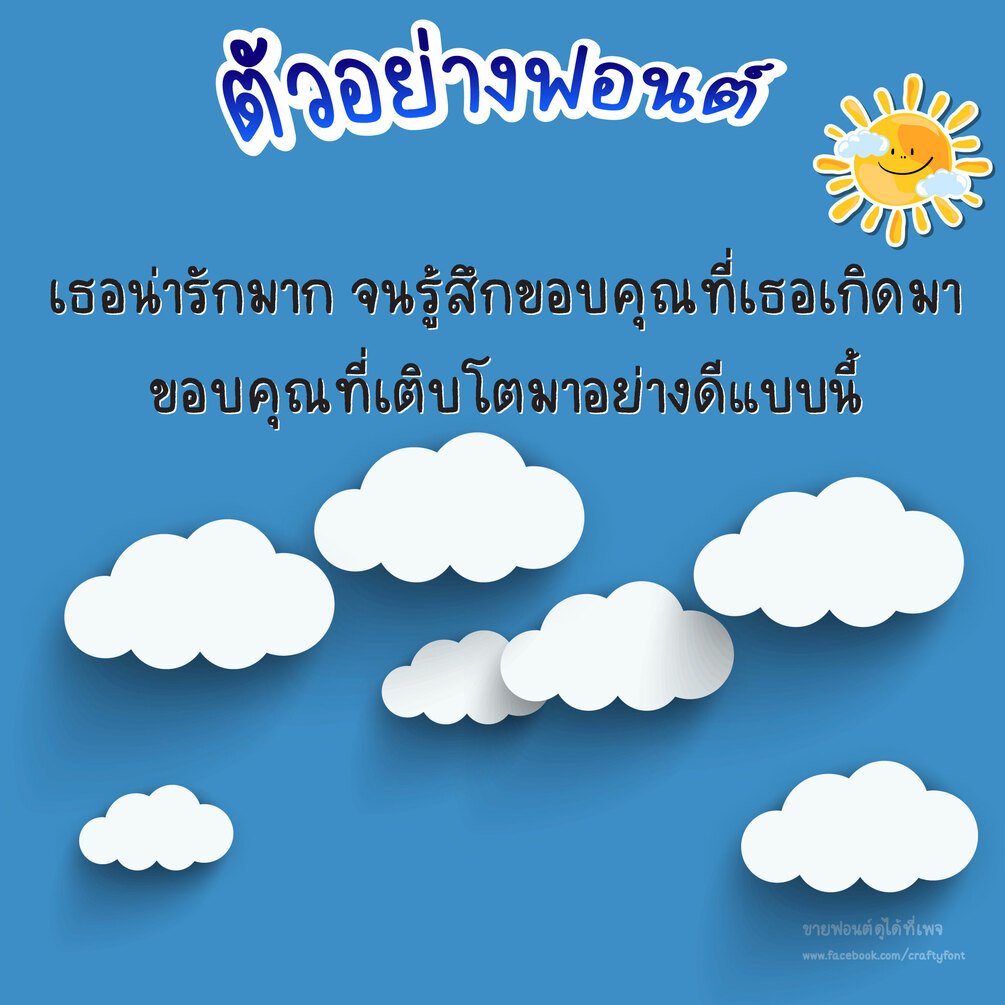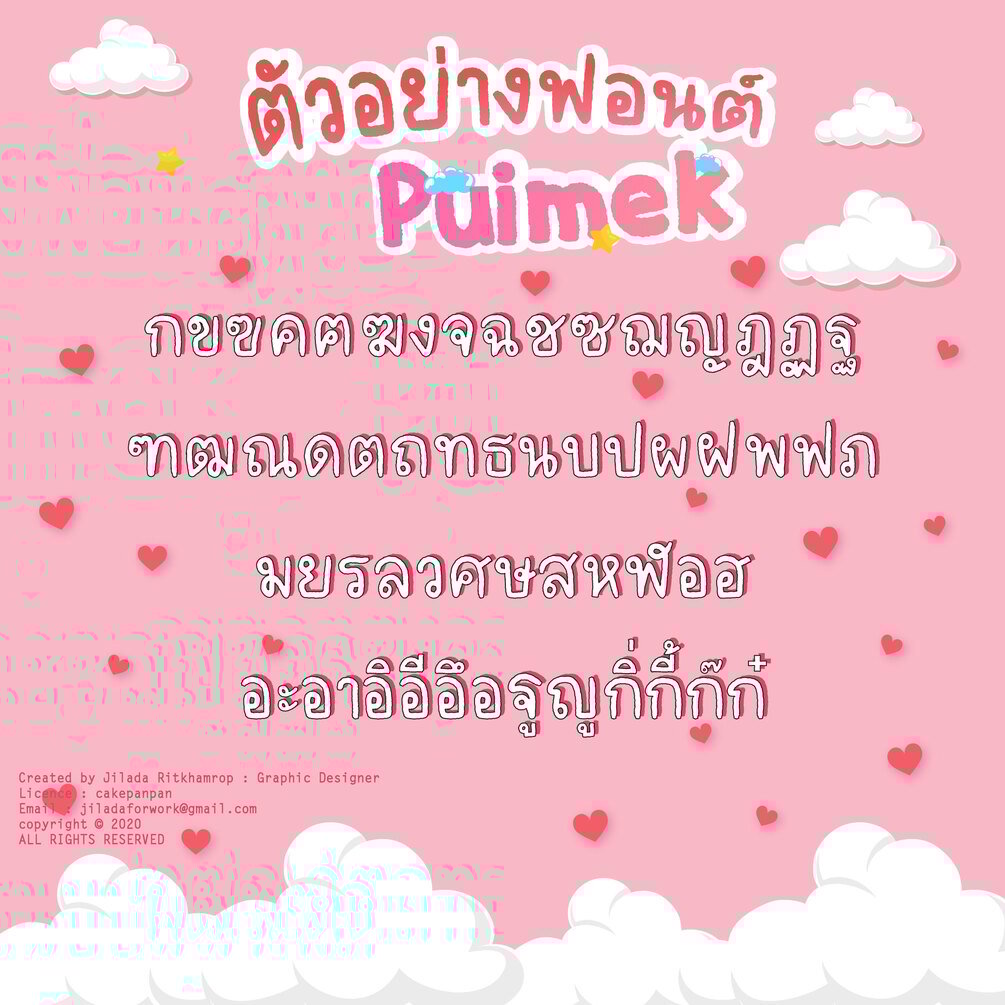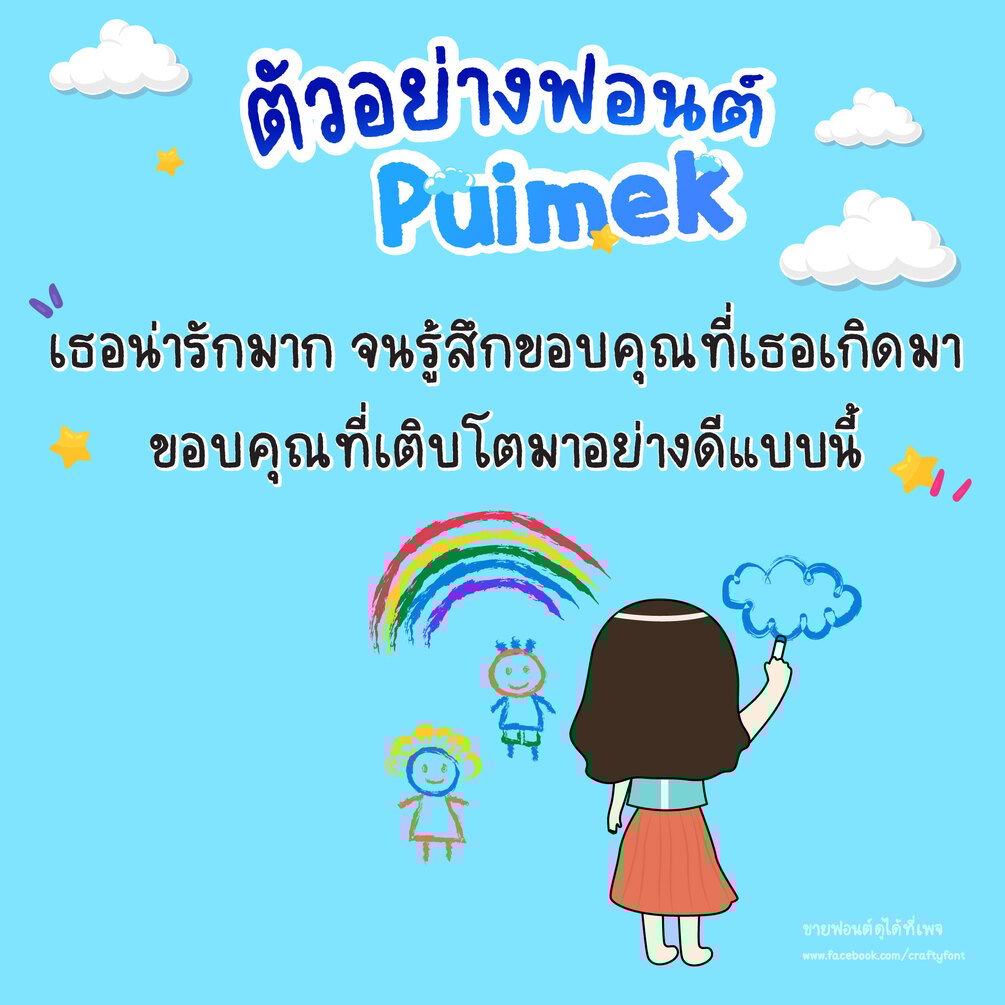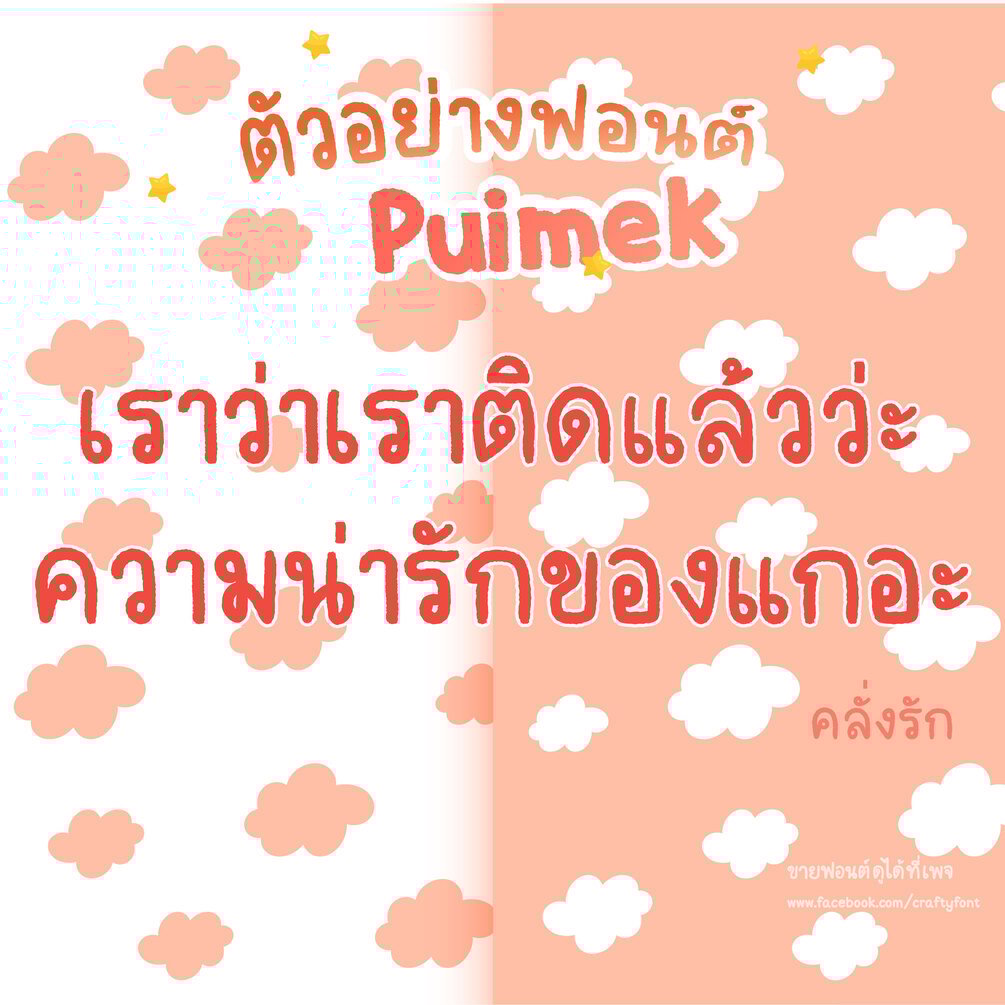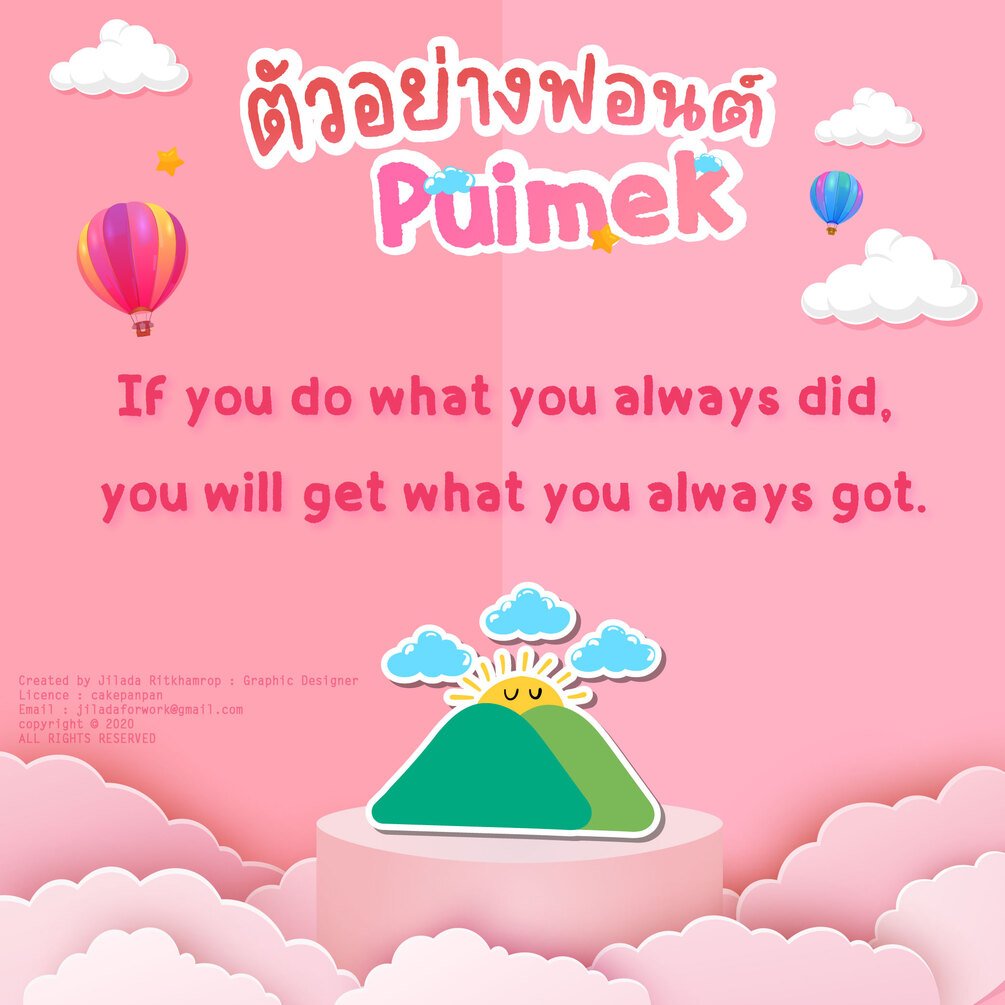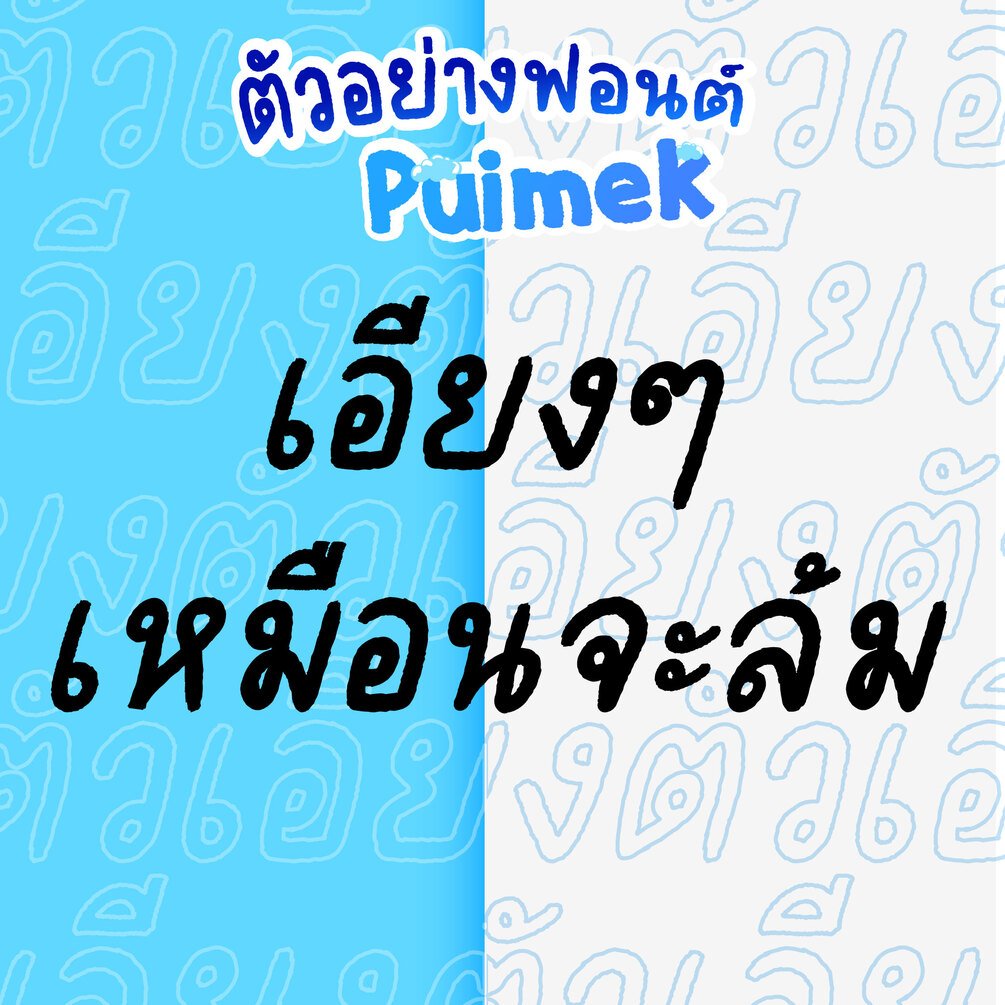
Puimek Font (ฟอนต์ปุยเมฆ)
ฟอนต์ปุยเมฆ ล่องลอยไปบนฟ้า~ ☁️🌥️ ใช้ได้ทั้งภาษาไทยและภาษาอังกฤษ
**ขอบๆ ตัวอักษรจะหยึกหยักเหมือนก้อนเมฆน้า ใน artwork อาจจะดูไม่ค่อยชัดฮะ